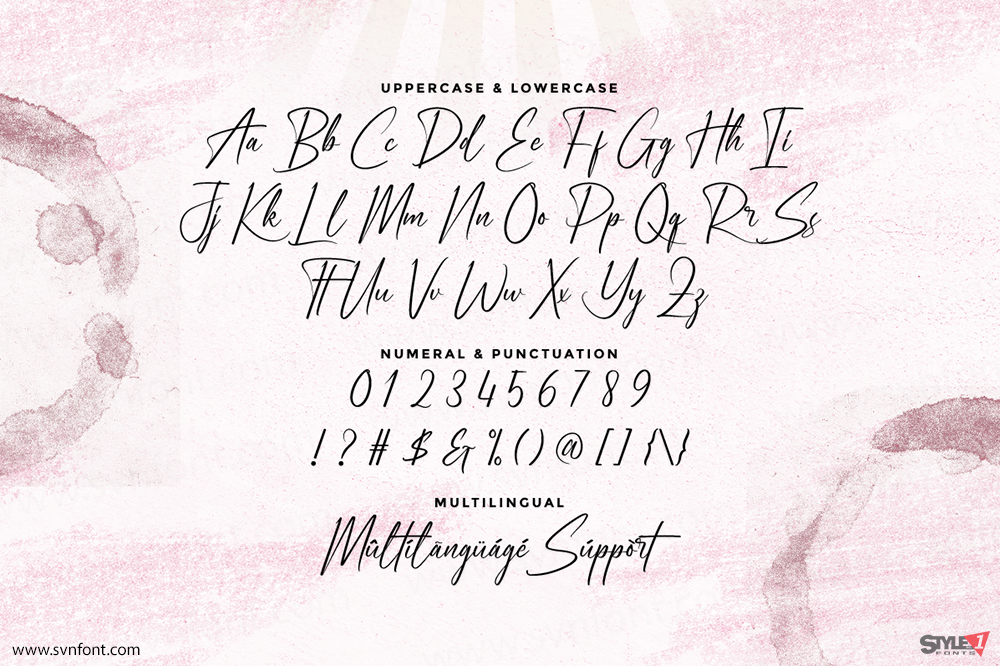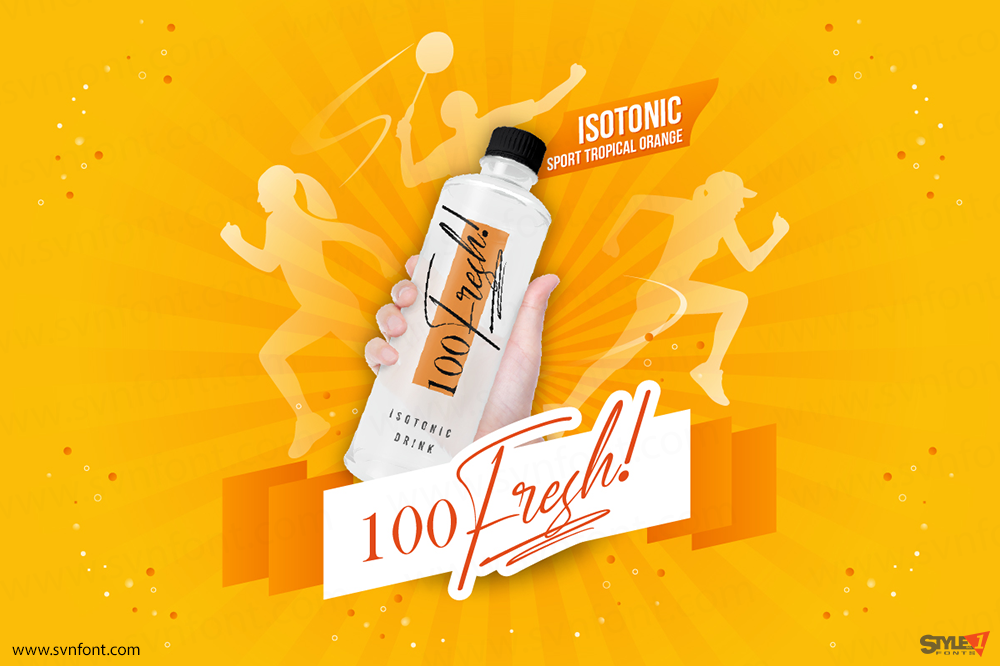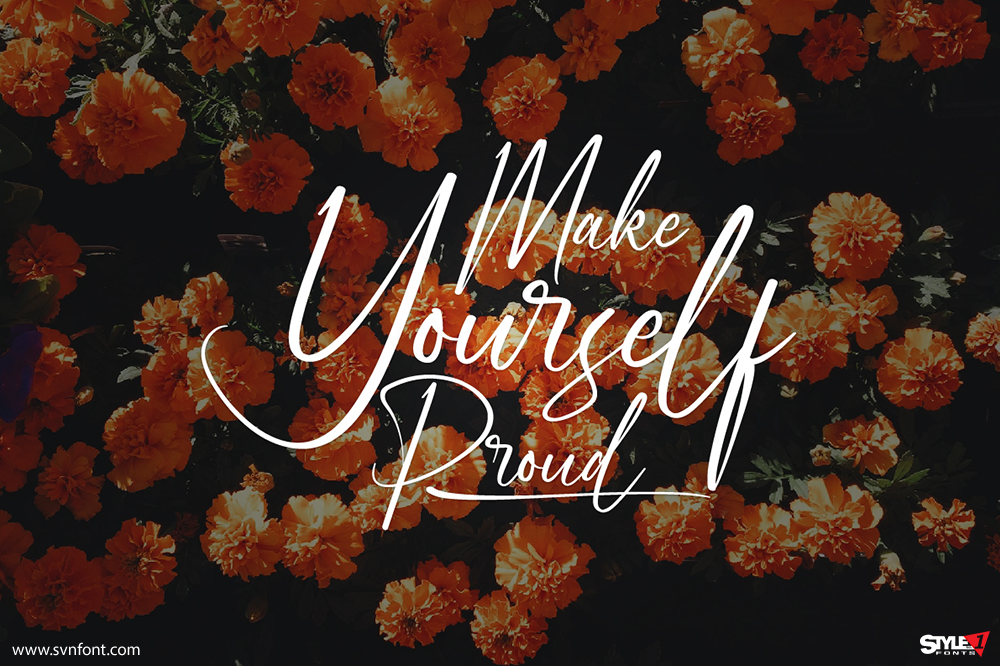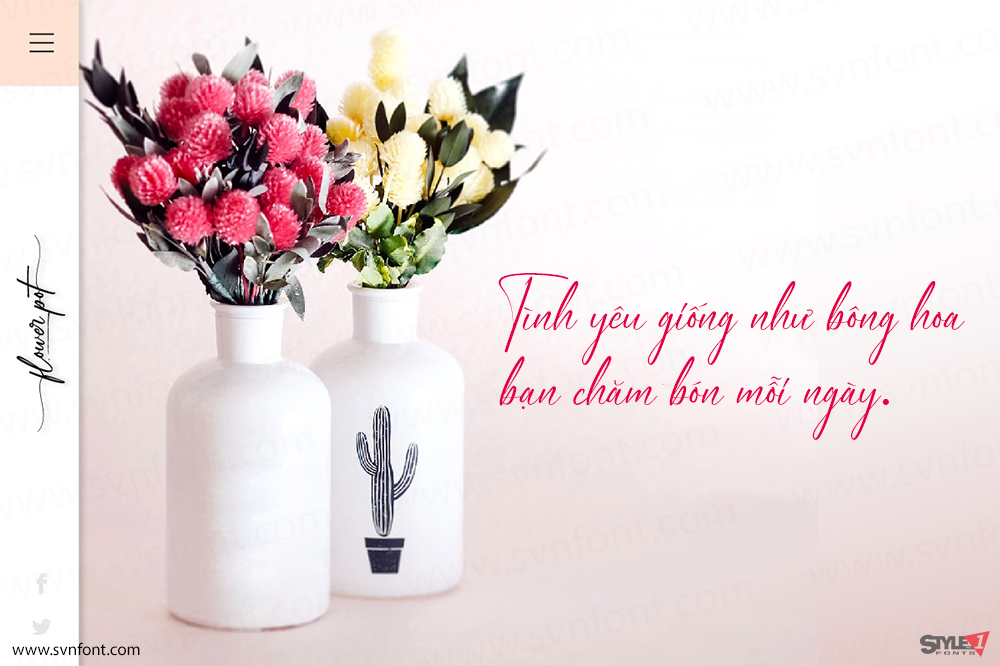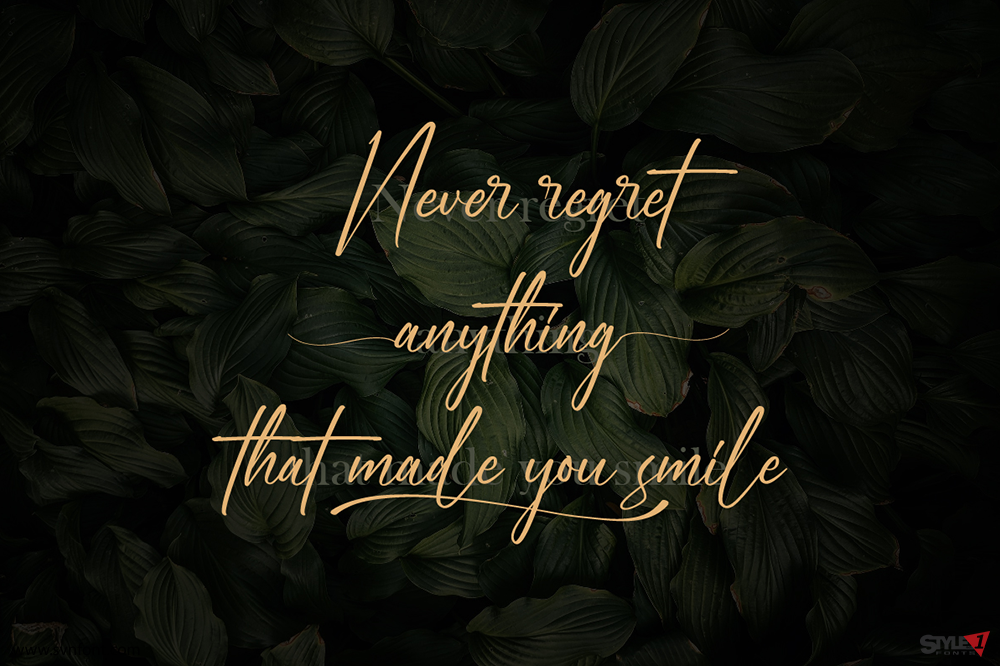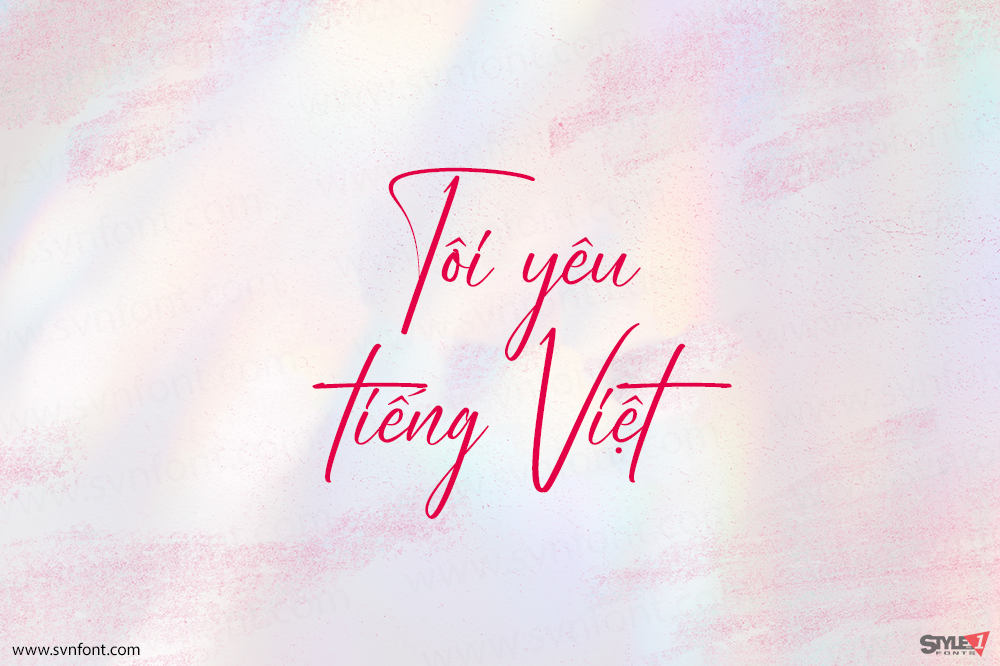
Manchester Park là một font script huyền ảo, được chế tác tỉ mỉ với nét thanh lịch và tinh tế. Font được PUA encoded, cho phép bạn dễ dàng truy cập toàn bộ glyph và ligature đặc biệt mà không cần thao tác phức tạp.
Nhà thiết kế: Widiyanti & Sarah Suci P
Nhà phát hành: Noahtype